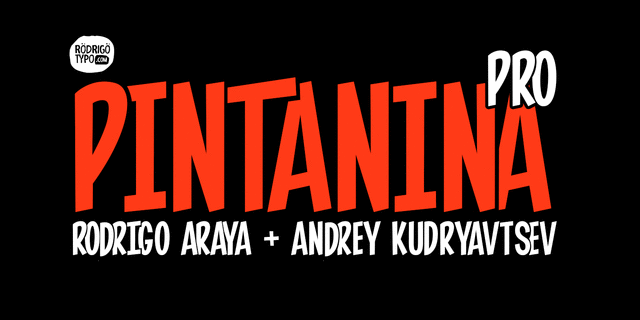
Шрифт Pintanina был разработан в 2013 году и имел много альтернативных символов в качестве лигатур. Это очень сжатый заголовочный шрифт, основанный на комиксах Кондорито. В последствии Pintanina была тщательно доработана, также добавлена кириллица и греческий алфавит.
Шрифт разработали Родриго Арая Салас при участии Андрея Кудрявцева в 2015 году.
Ассоциации c начертанием Pintanina Pro RegularКачества и характер:
выразительный, забавный, высокий, ироничный, здоровый, бодрый, характерный, праздный, гуляющий, балованный, гладкий, интересный, студенческий, тусовочный, прикольный, динамичный, живой, непоседливый, неформальный, молодежный, броский, веселый, задорный, смешной, радостный, игривый, озорной, подвижный, оригинальный, свежий, заметный, детский, карикатурный, мультяшный, остроумный, счастливый, праздничный, творческий, звонкий, чистый, твердый, позитивный, свободный, мотивирующий, смелый, громкий, острый, артистичный, яркий, активный, внушительный, тесный, уверенный, сильный, устойчивый, революционный, важный, рабочий, амбициозный, гордый, резкий, уличный, кричащий
фаст фуд, лавка, граффити, приключения, развлечения, вечеринка, торговля, реклама, магазин, игра, детская книжка, лагерь, юмор, анимация, еда, закуска, отдых, цирк, мультфильм, шоу, кино, праздник, аттракцион, пицца, митинг, революция, видео, забастовка, протест, наклейка, стикер, супергерой, дискотека, аквадискотека Стилистика: